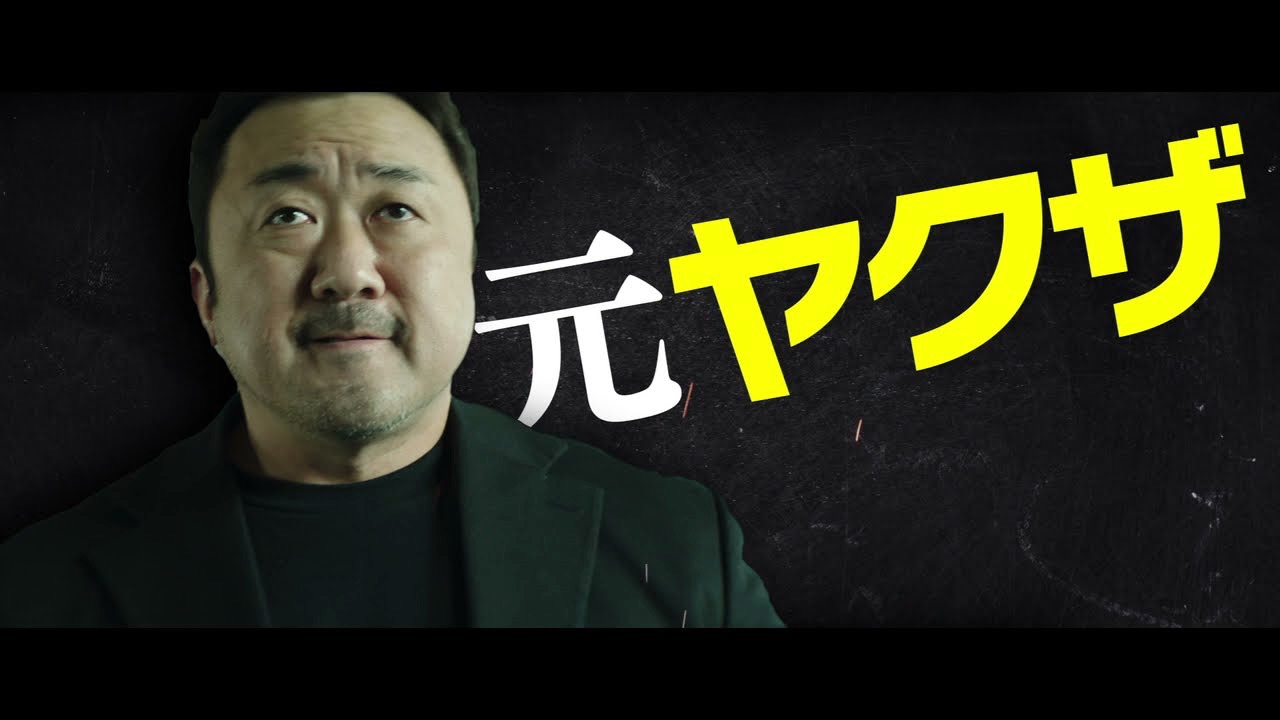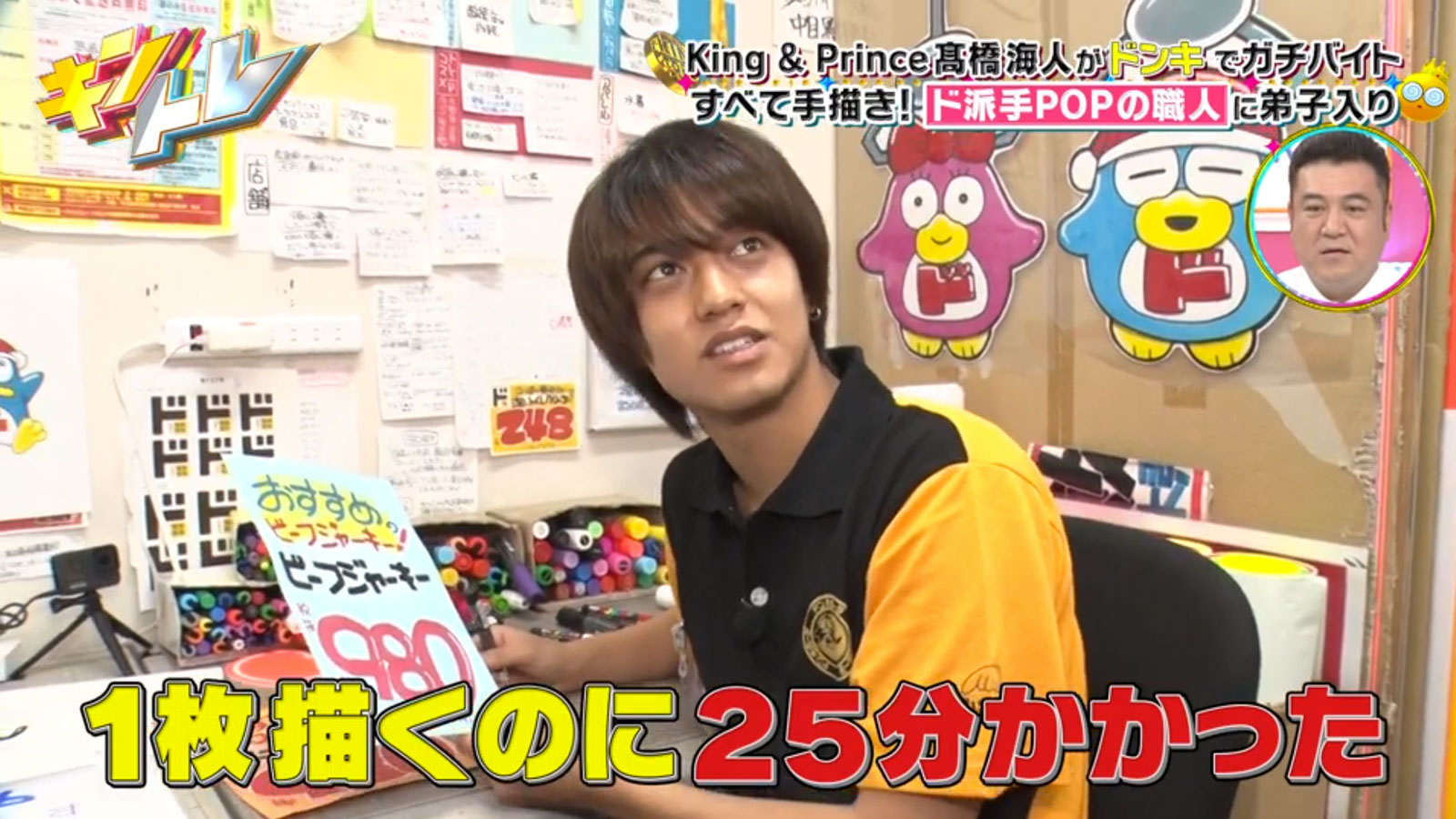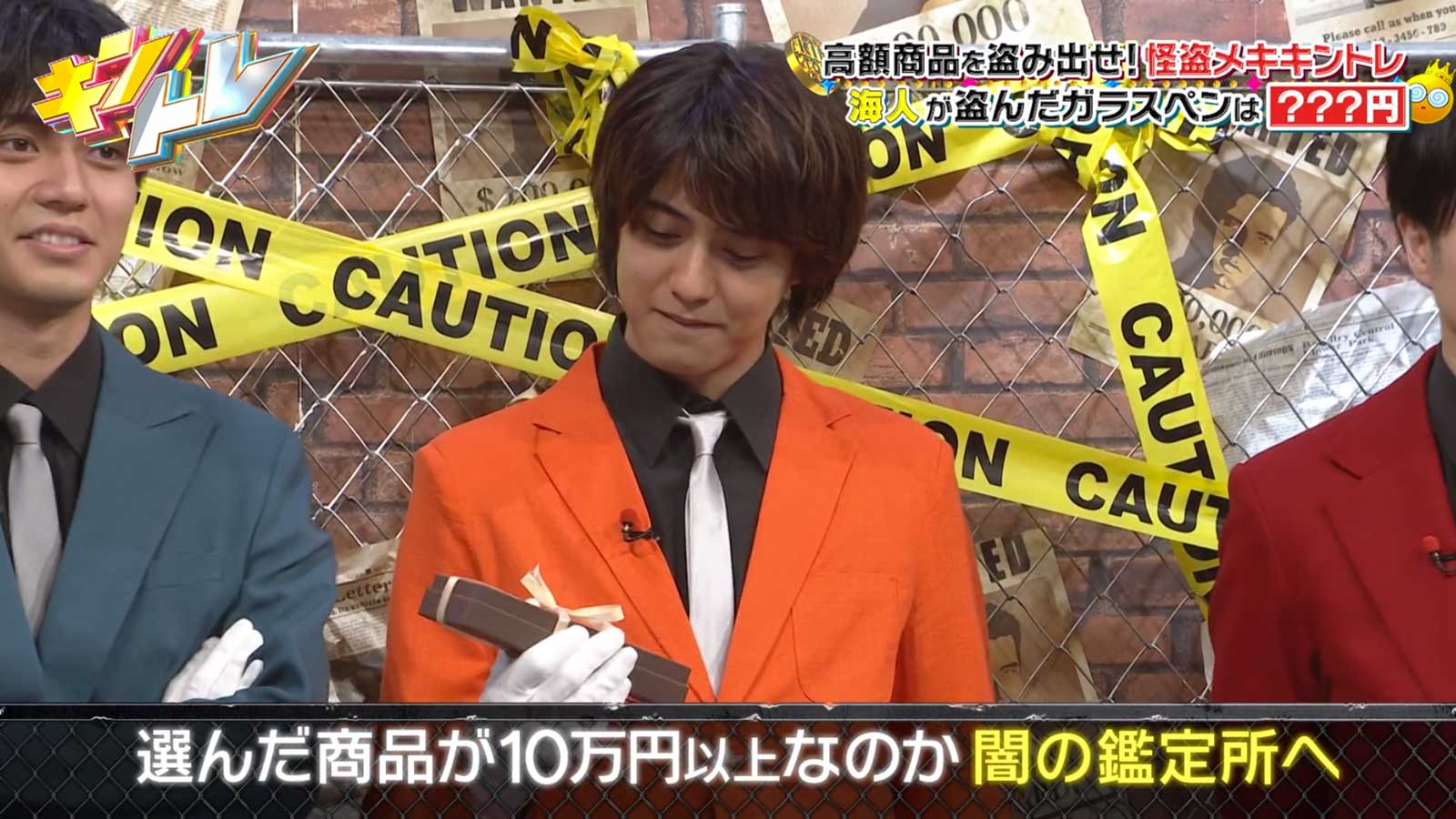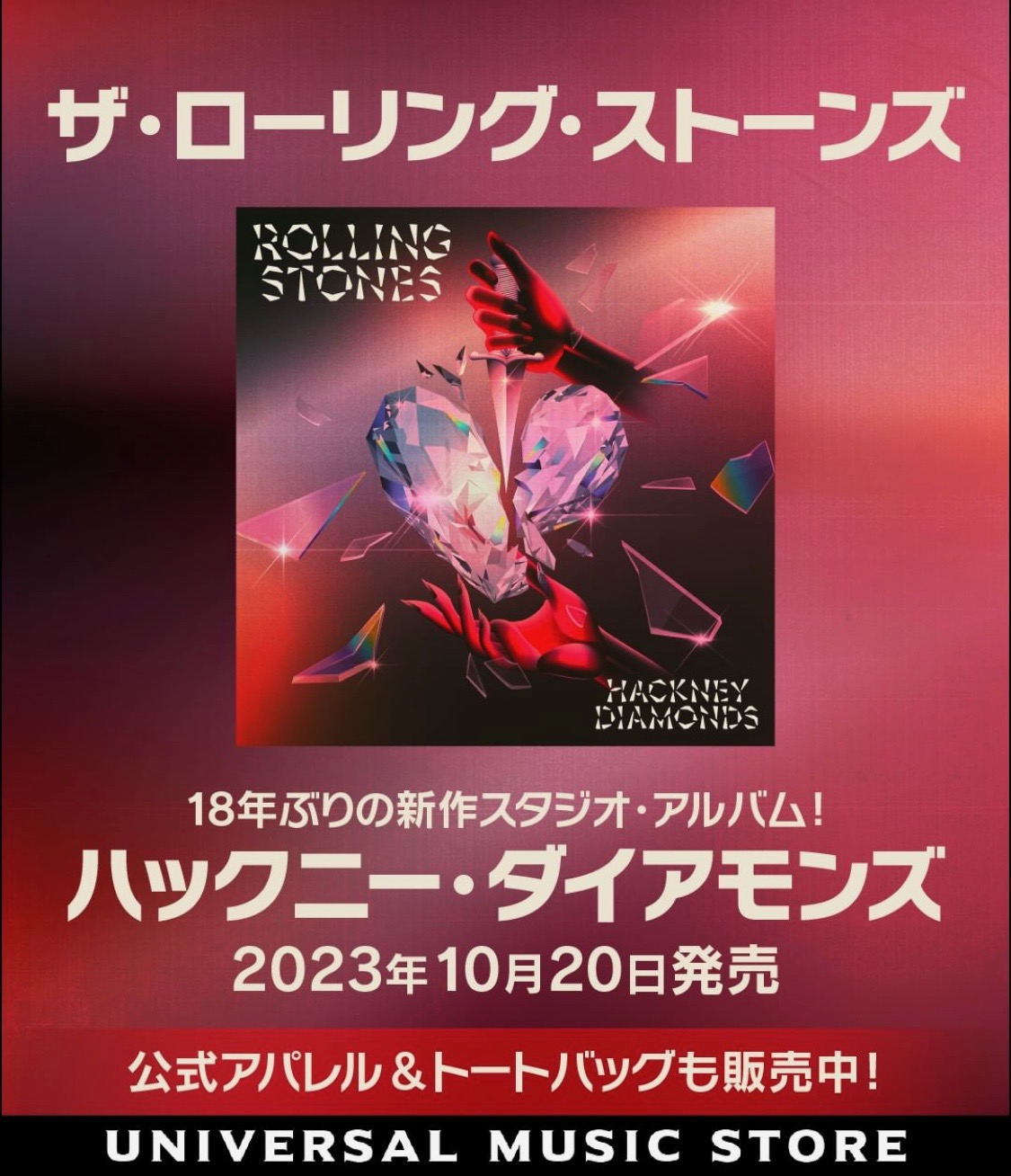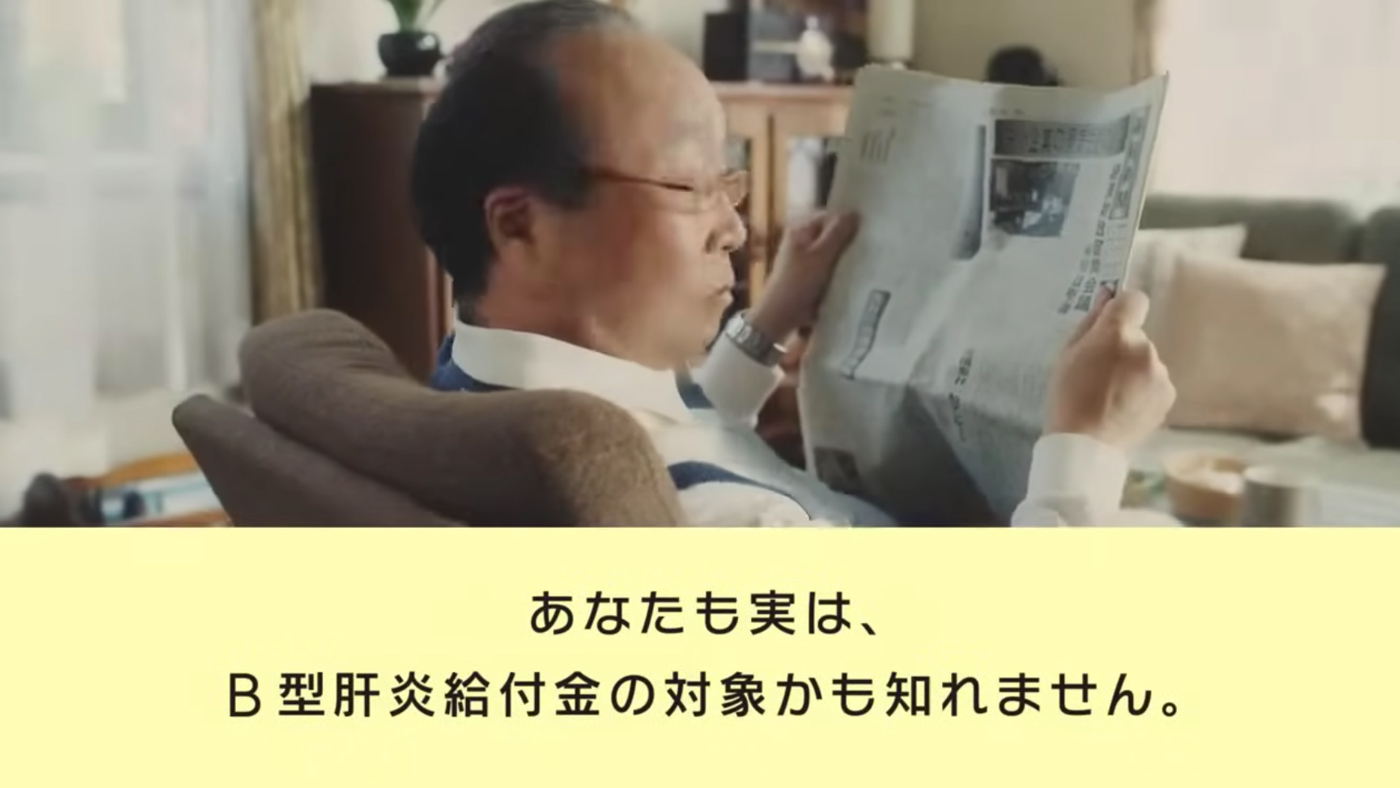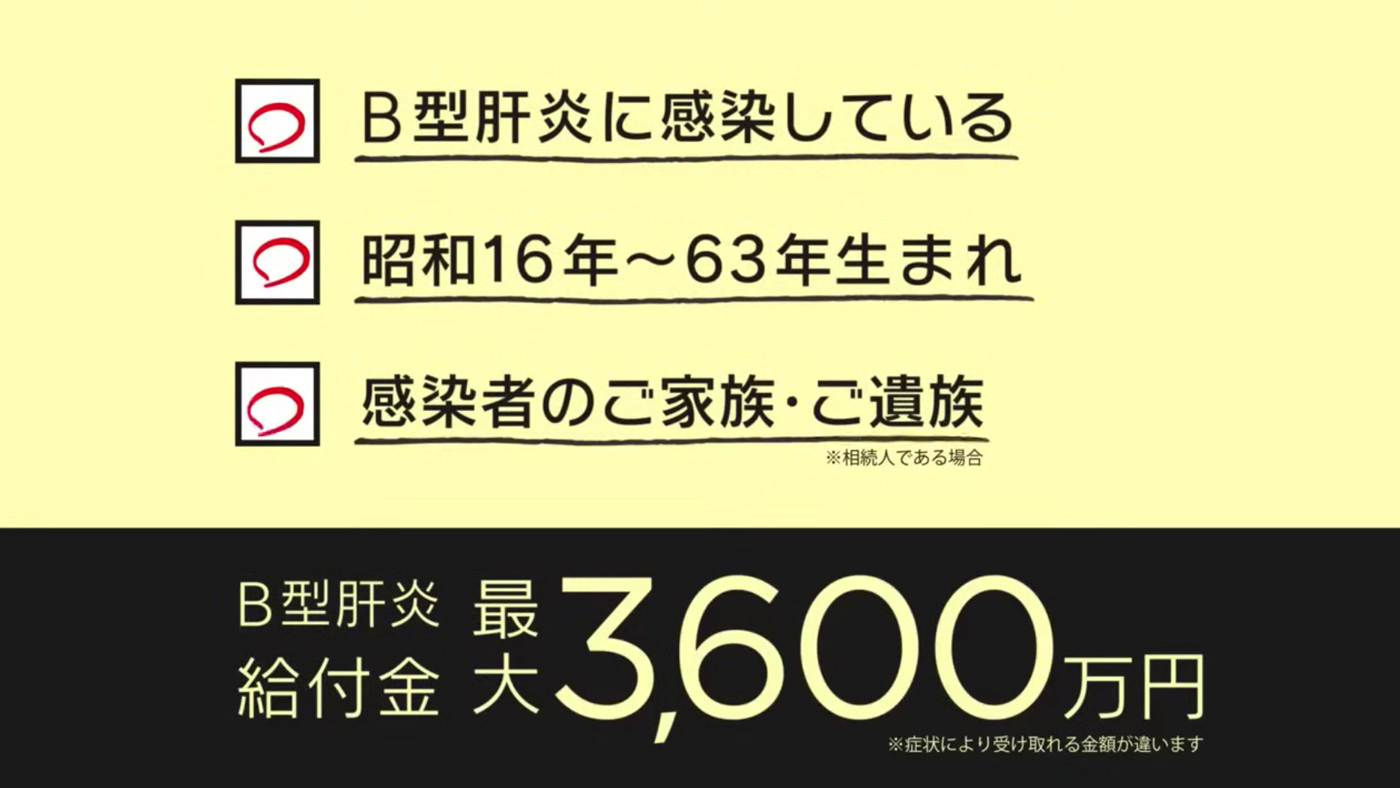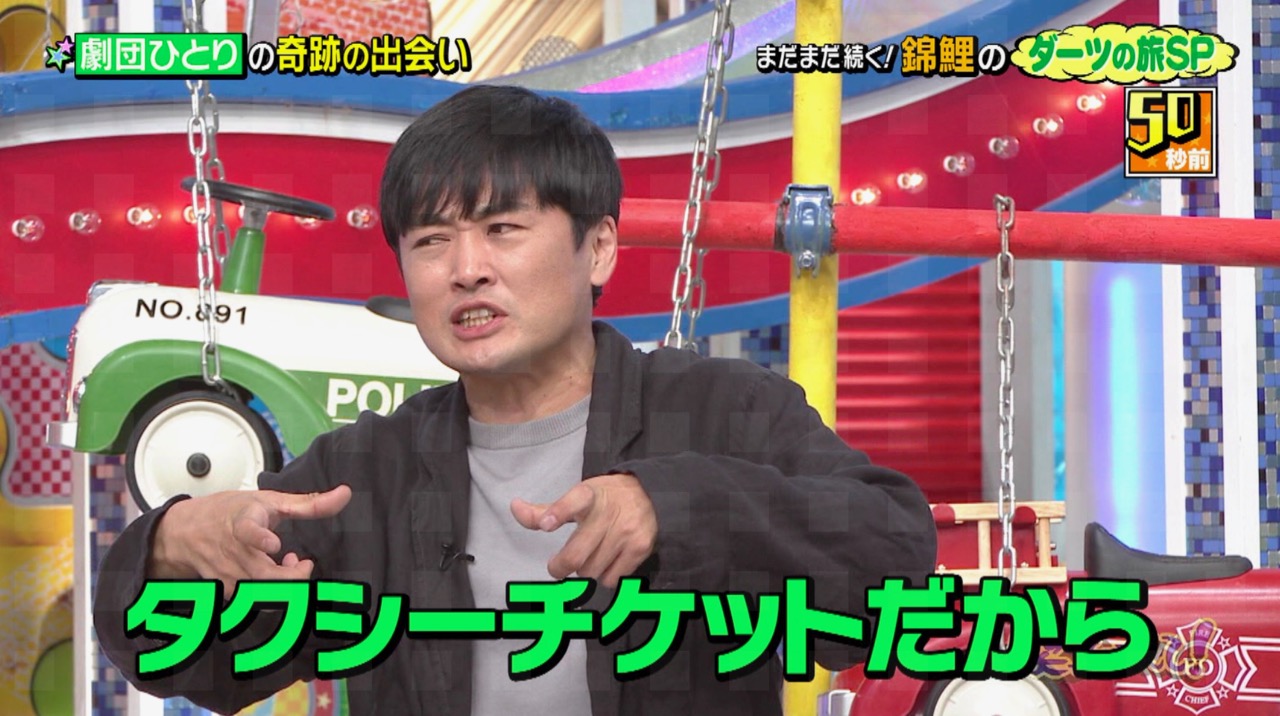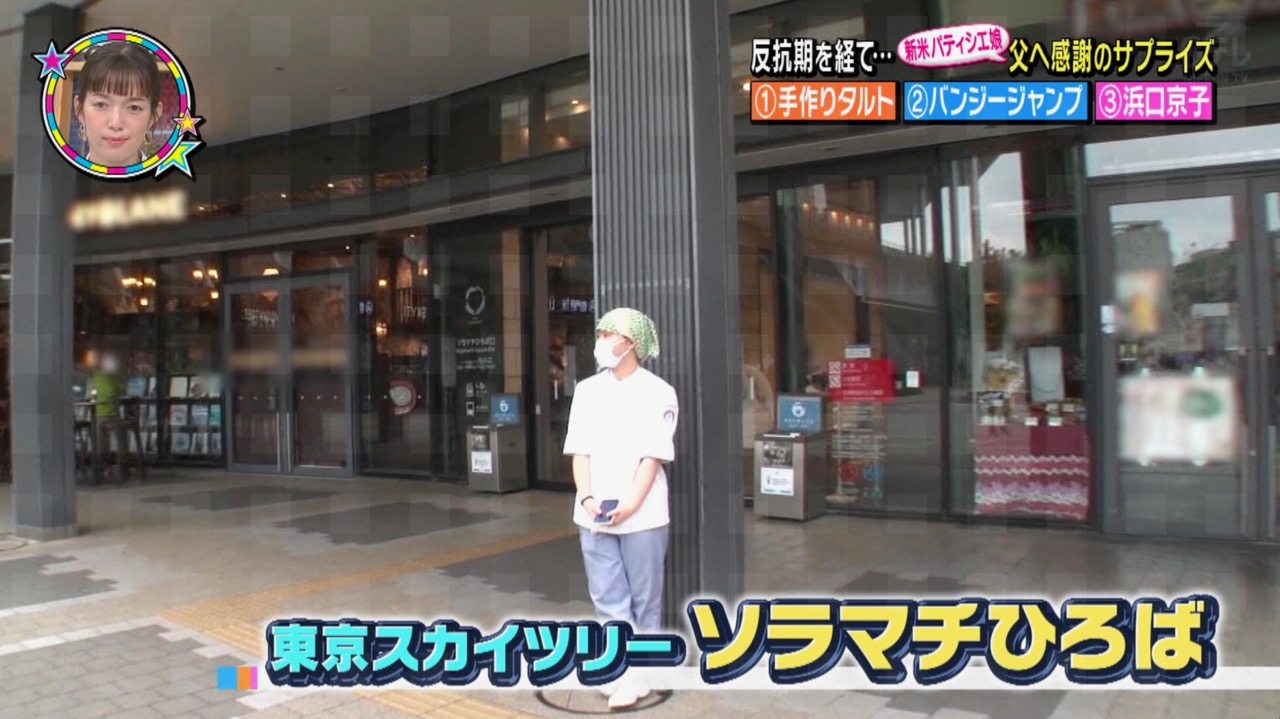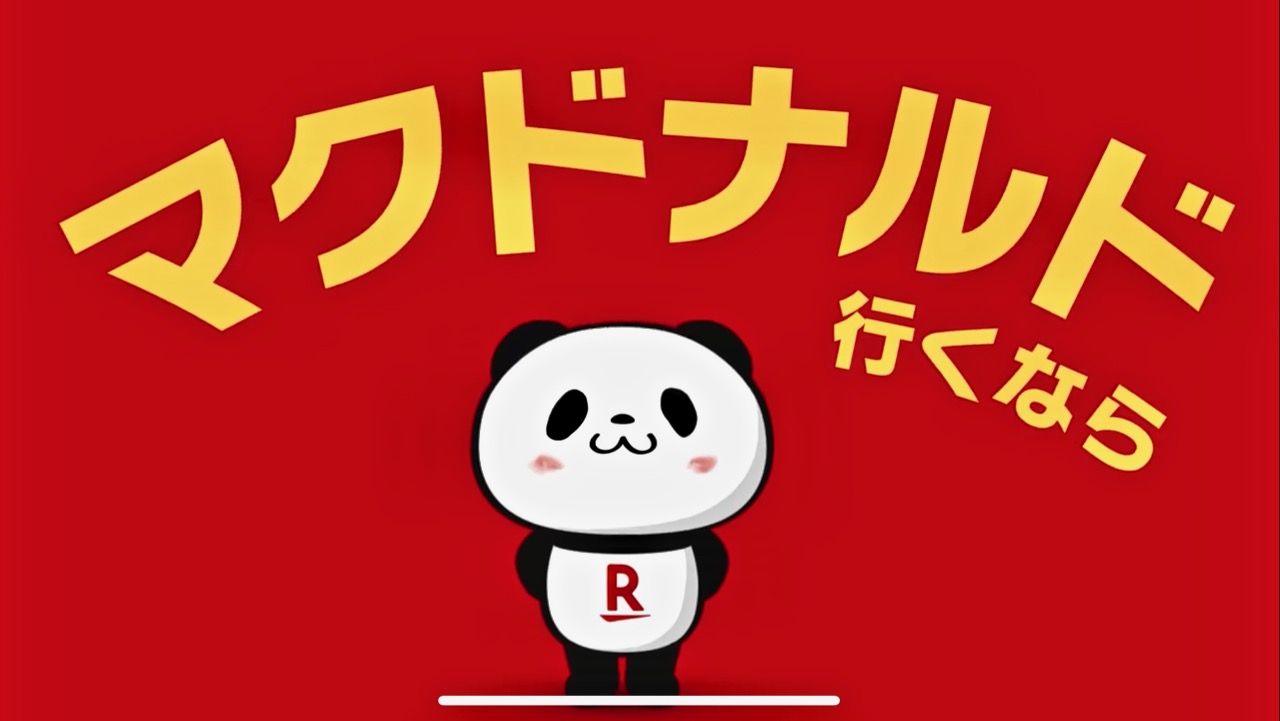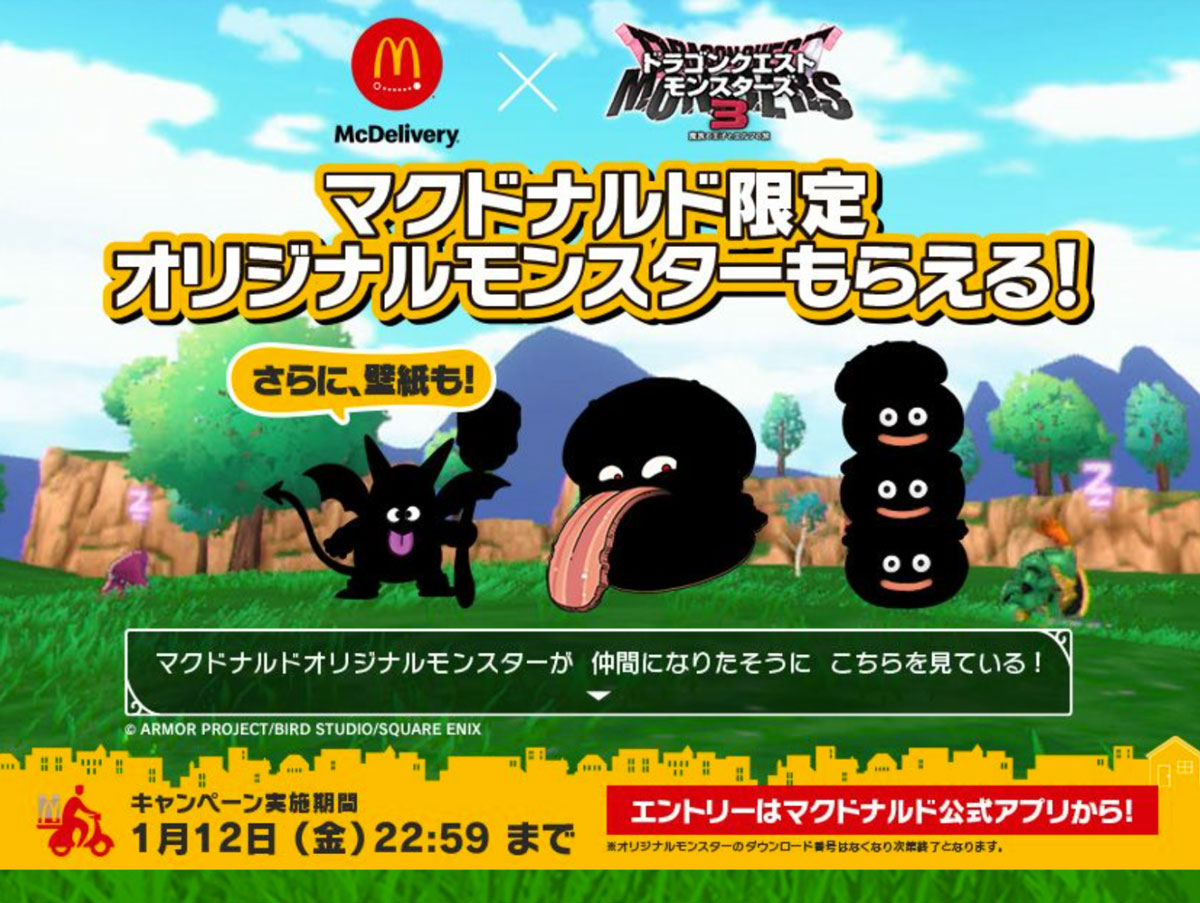
貸し倉庫 さとうゆたか
地下鉄日比谷線の隅田川鉄橋の南千住側にあるトランクルーム。
これは公式画像かな…。
テレビドラマ さとうゆたか
テレ朝系列「いつか、ヒーロー」。
YouTube動画内の字幕にて ぽーん
「にじさんじ公式切り抜きチャンネル」さんの動画でメインの字幕にニタラゴルイカが使われていました(動画編集の担当者の方が複数いらっしゃって、この方の動画にはニタラゴルイカが使われることが多そうです)
大きな看板に さとうゆたか
テレビや印刷分野だけでなく、街なかの看板などにも良く使われている。
アニメ「ポケットモンスター」のPV takumi
放送中のアニメ「ポケットモンスター」の新章「メガボルテージ」のPVより。
同作のキャラ紹介PVでも同様にニタラゴが使われています。
テレビ番組 さとうゆたか
フジテレビ「呼び出し先生タナカ」。
もうひとつ。
最後にこれも。
マクドナルド広告 さとうゆたか
相変わらずマクドナルドの広告には、ニタラゴ書体が使われている。
もうひとつ。
本の表紙 さとうゆたか
書名:なにをしているの?
著者:オリビア・コスノー、ベルナール・デュイジット
発行:大日本絵画
広告画像 さとうゆたか
ニタラゴルイカの使用例。
もうひとつ。
病院で… さとうゆたか
年に一度の特定検診に行った、近所の病院に貼られていたポスター。